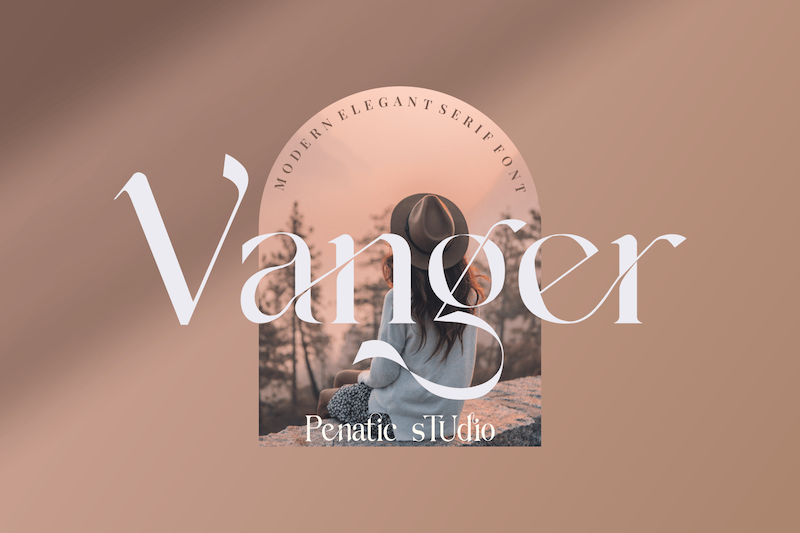
لیدیز از جنتلمن! معرفی میکنم: فونت زیبا، خوش رنگ و لعاب و خوشاستیل ونگر با تعداد زیادی کاراکترهای پیوندی (لیگچر) منحصربهفرد، حالتهای جایگزین (آلترناتیو) و پشتیبانی از چند زبان.
فونت ونگر ما را با سبک کلاسیک و مدرن خود تحت تأثیر قرار میدهد، که این امر با دسترسی به فونتهای جایگزین متعدد در ابزار اُپنتایپ امکانپذیر است.
طبقهبندی: سریف
فاصلهگذاری: نرمال